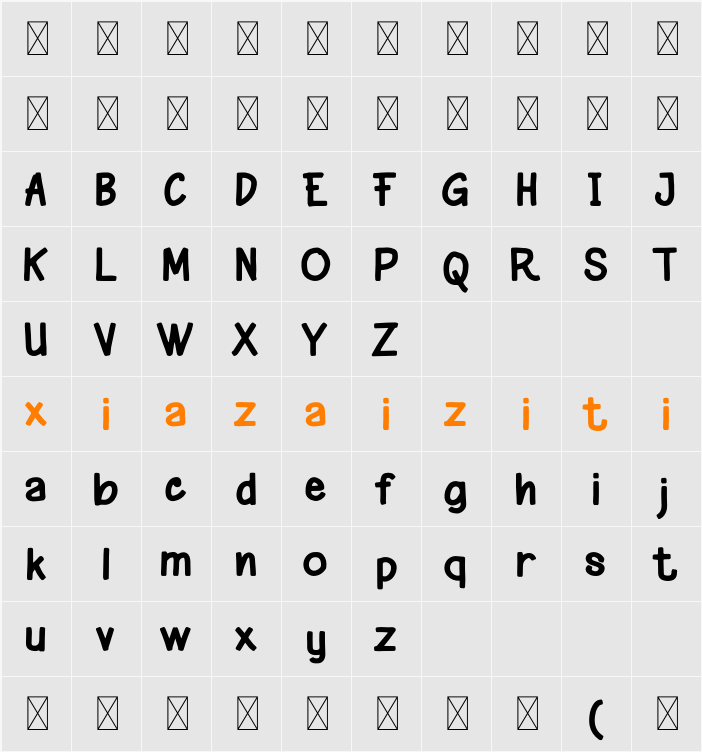
With Logica
With Logica,这款字体结构工整、笔画清晰,兼顾美观与易读性,适用于标题、正文、海报、包装、LOGO 等多种场景。字形优雅稳定,风格百搭耐看,适配日常排版与创意设计,让文字呈现更舒适、更具质感。With Logica一笔一画,皆是细节,以均衡的比例、流畅的线条打造舒适视觉体验,字形端正大气,风格简约现代。无论是商业设计、品牌宣传还是日常排版,都能轻松驾驭,让文字更有格调与力量。With Logica字体下载。
• 设计师: Rachmad Bagus Fatchi